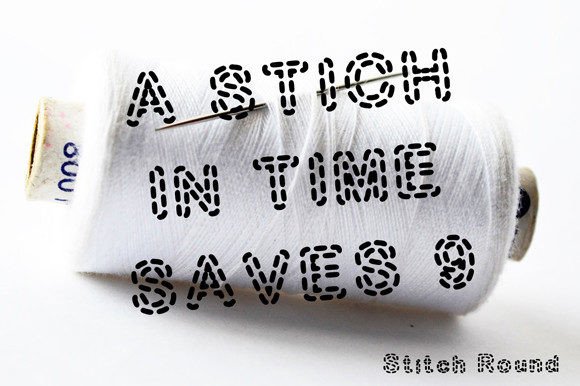
SVG Font Bundle Stitch Rounded
SVG Font Bundle Stitch Rounded – A Escolha Perfeita para Criativos
Se você é artista, designer ou crafter, o SVG Font Bundle Stitch Rounded chega como a solução definitiva para dar vida às suas ideias. Esta coleção de SVGs foi pensada para quem busca qualidade profissional, versatilidade e um toque único que faz qualquer projeto se destacar.
Por que este bundle se destaca?
- Design exclusivo e arredondado – As fontes têm um estilo “stitch” que lembra costura, perfeito para projetos artesanais e digitais.
- Escalabilidade sem perda de qualidade – Como são arquivos SVG, você pode ampliar ou reduzir para usar em camisetas, canecas, pôsteres, adesivos e muito mais.
- Facilidade de uso – Cada letra vem como um único vetor, pronto para ser arrastado para o seu layout em segundos.
Aplicações práticas que encantam
Com este bundle, você pode:
- Personalizar camisetas e hoodies com frases em estilo costurado.
- Decorar canecas, copos e garrafas para presentes únicos.
- Criar pôsteres e quadros decorativos que chamam a atenção em qualquer ambiente.
- Adicionar detalhes digitais em sites e blogs para um visual criativo.
- Produzir adesivos, etiquetas e scrapbooks com acabamento profissional.